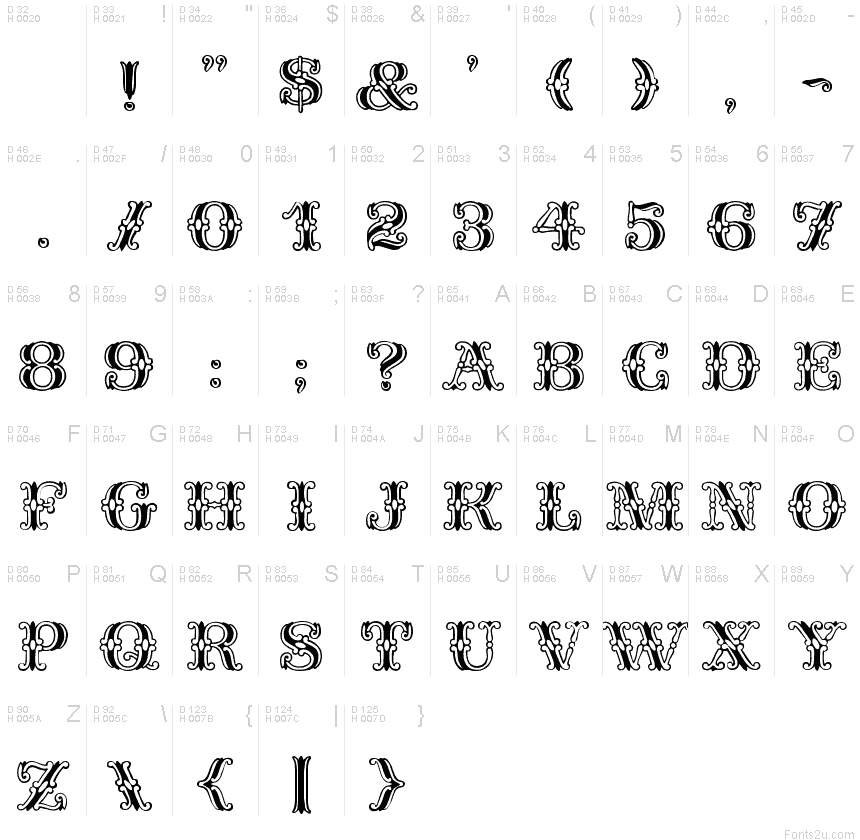
Spatz Plain
由 i1993 LORVAD 设计的 Spatz Plain 是一款免费的 Art Nouveau(新艺术运动)风格显示字体。它那蜿蜒的植物形态让人联想到锻铁工艺和古籍的标题页。通过循环的笔触、泪滴状的花蕾和圆润的笔端,这款字体呈现出鲜明的装饰美感,而非结构功能。
它非常适合用于海报标题、书籍封面、咖啡馆菜单、活动邀请函和字母组合,在那里,一个装饰性的首字母能够起到极佳的视觉点缀作用。作为一款免费字体,它在短行、标题卡和首字下沉排版中表现最为出色,因为这些旋涡状的细节需要足够的空间来展现其如藤蔓般的律动。